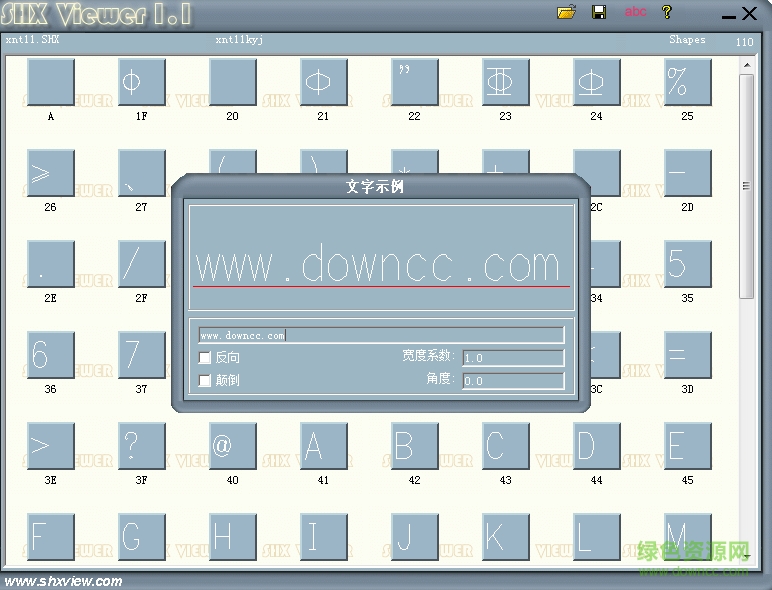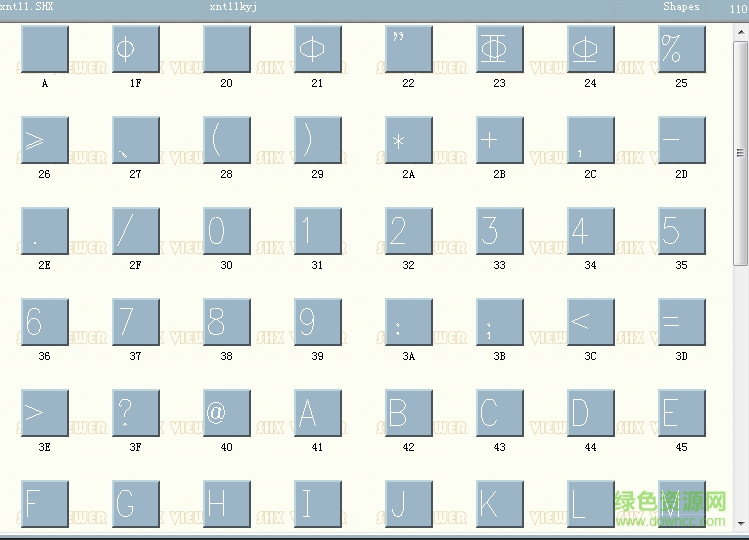
xnt11.shx
xnt11.shx字體是一款autocad的專用字體,shx字體雖然沒有一般的windows字體華麗漂亮,但該類字體縮放方便,電腦顯示效果精細(xì),設(shè)計(jì)更便捷,有需要者快來綠色資源網(wǎng)下載吧!
shx字體介紹
cad里所稱的shx字體和大字體(也叫bigfont),都是autocad專用專有的字體。大字體也是shx字體,是shx字體的一種特殊形式。
xnt11.shx字體特點(diǎn)
特殊性:集成鋼筋1-4級(jí)鋼筋符號(hào);2次方上標(biāo)符號(hào);羅馬字2、3符號(hào);主要占用左鍵盤換房鍵位字符。